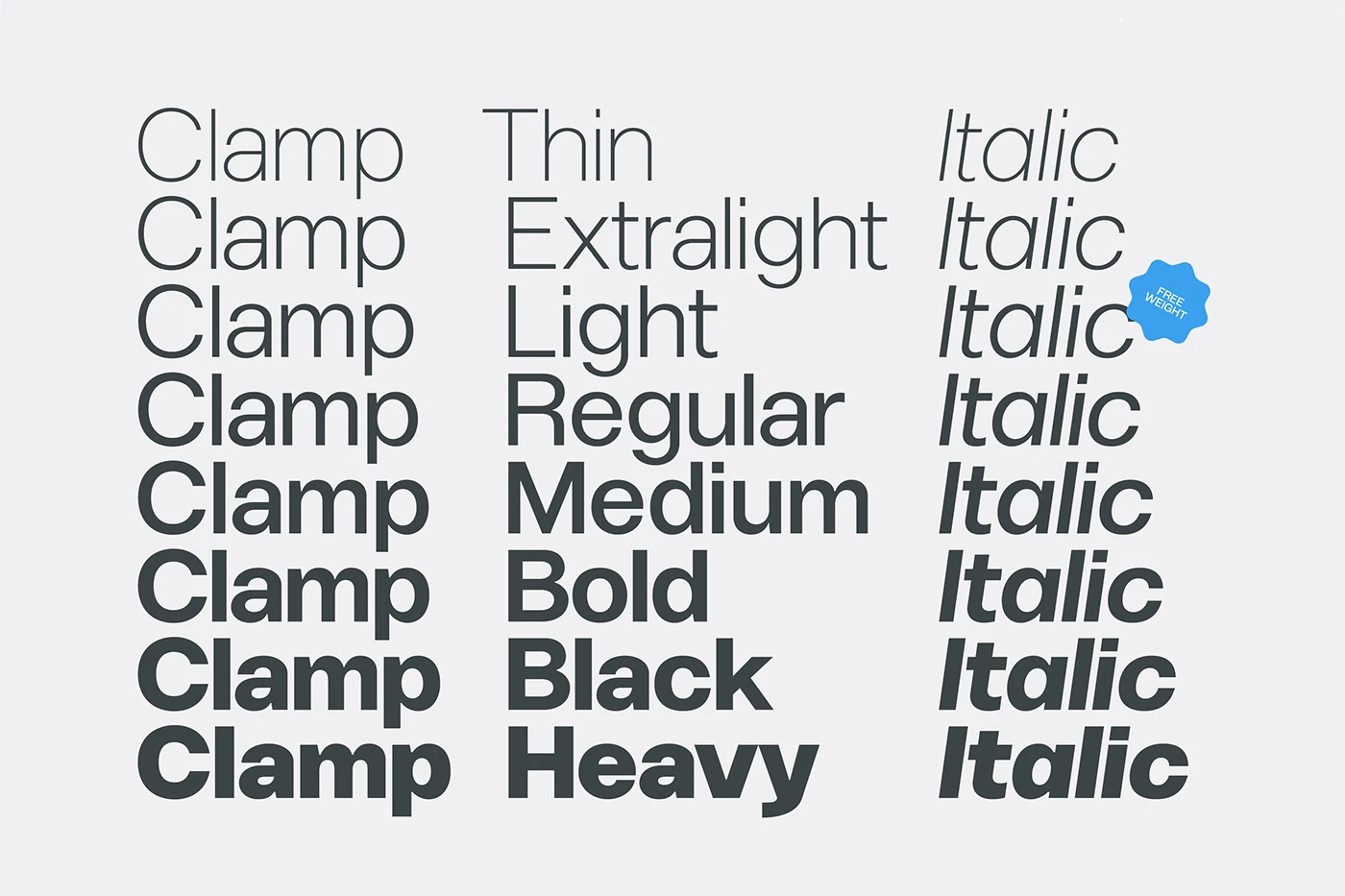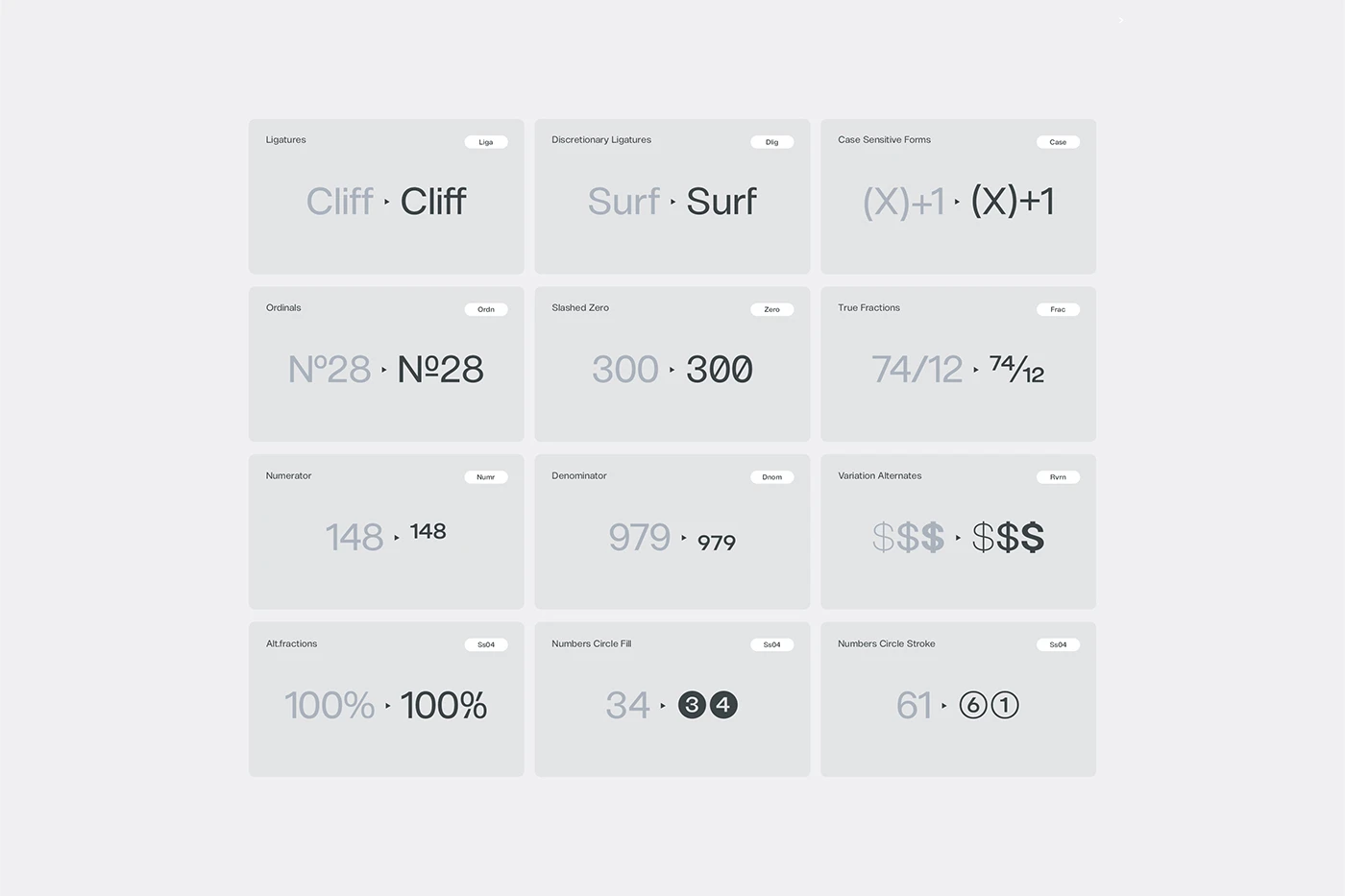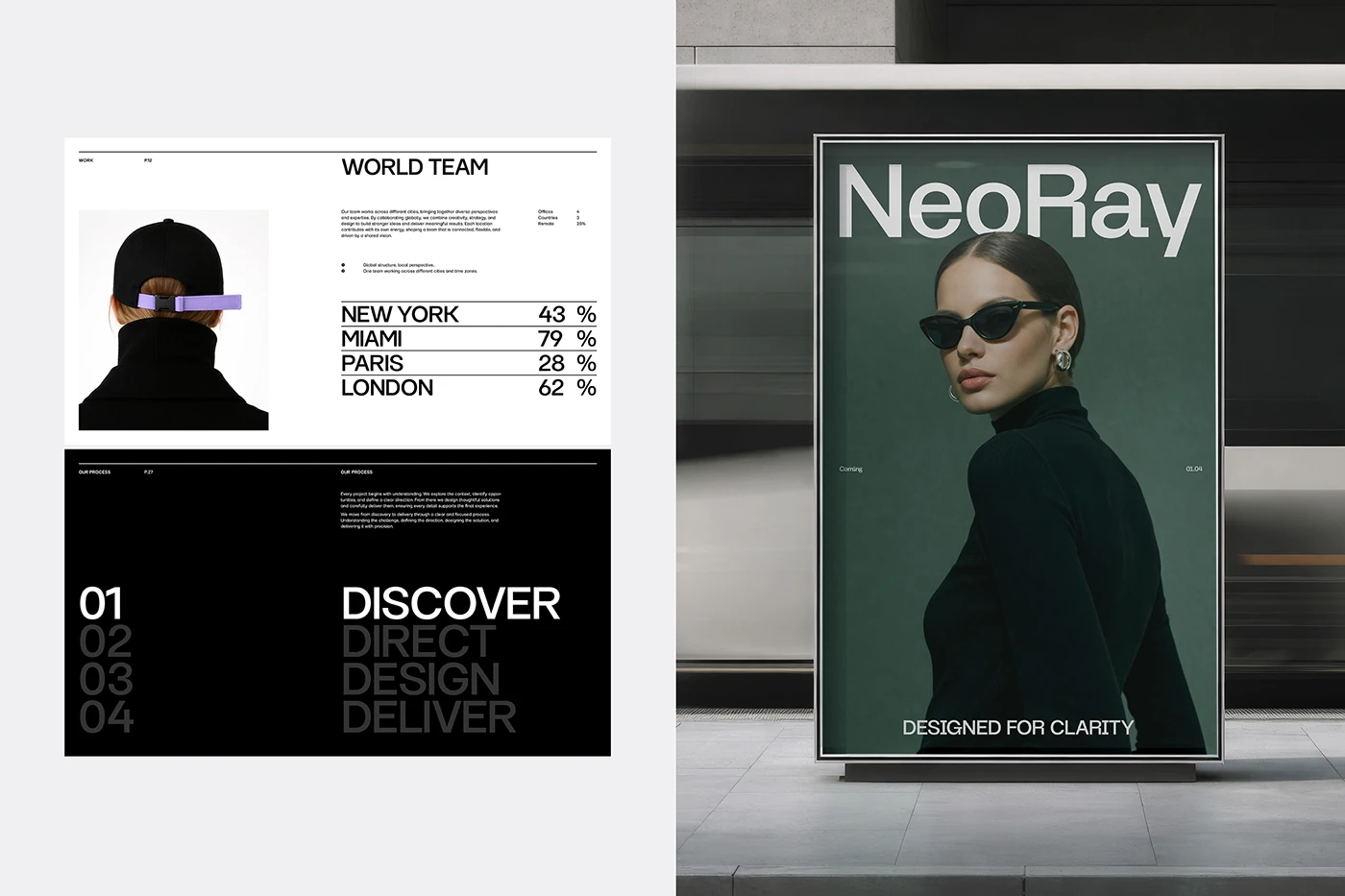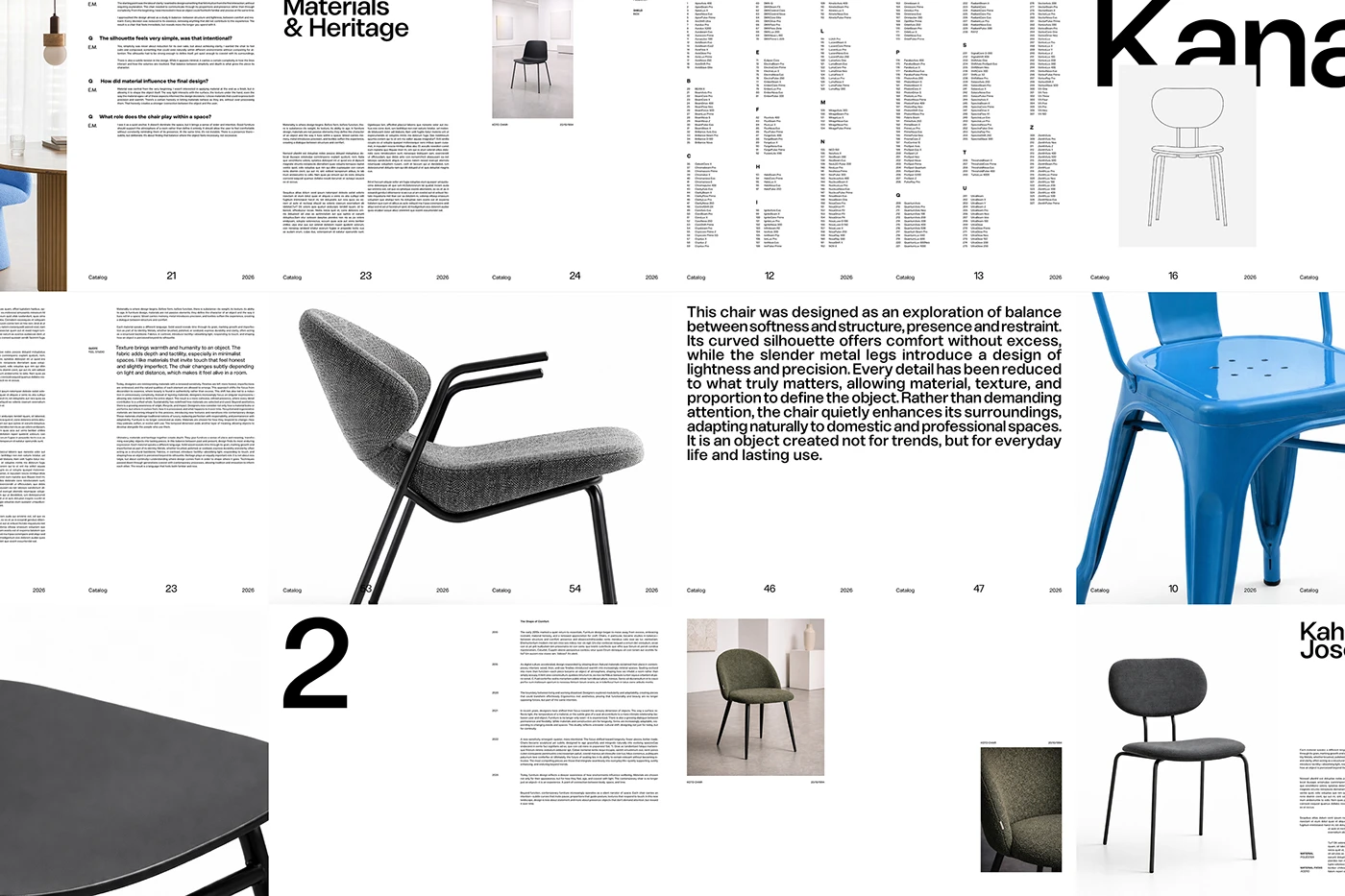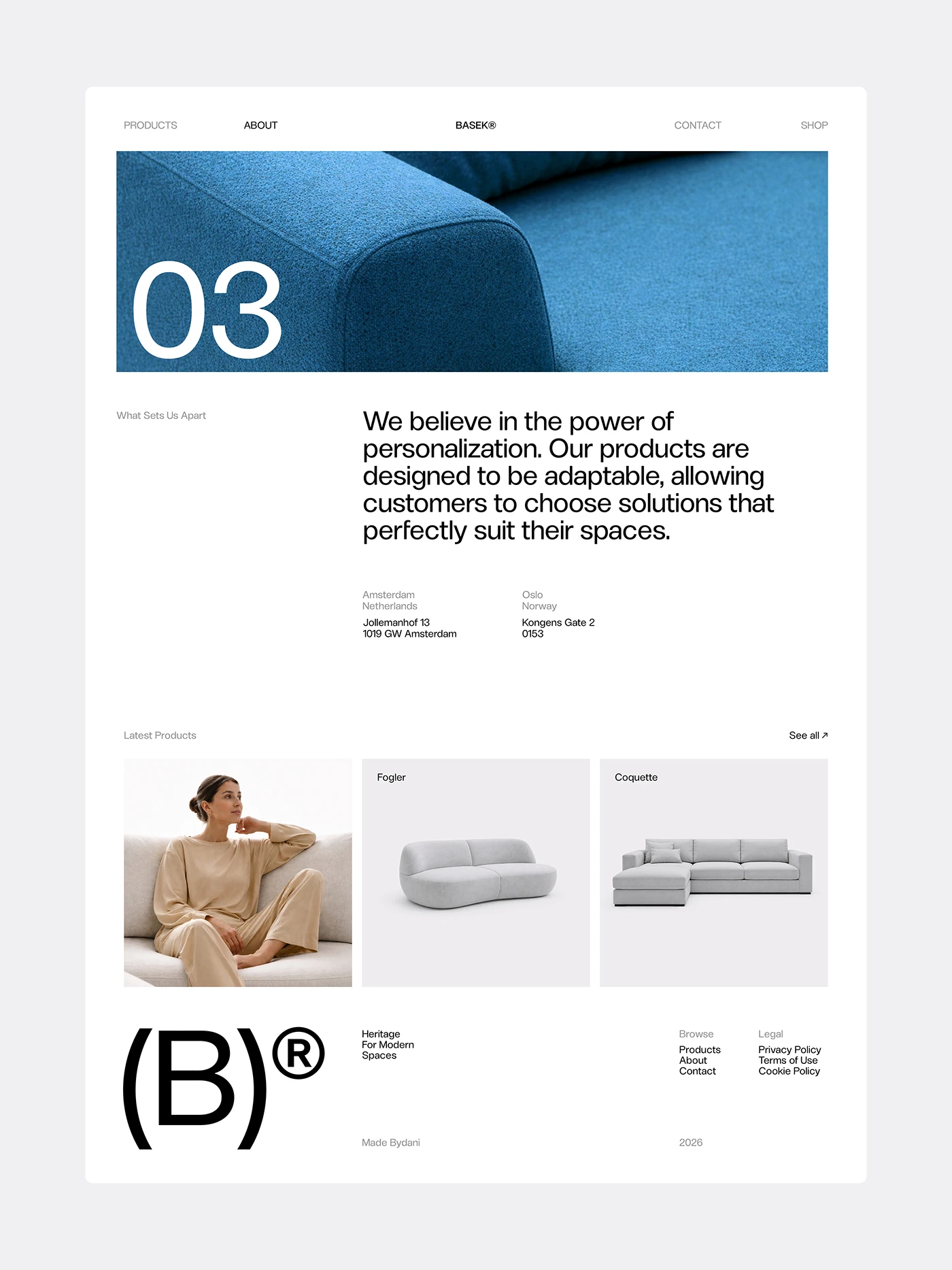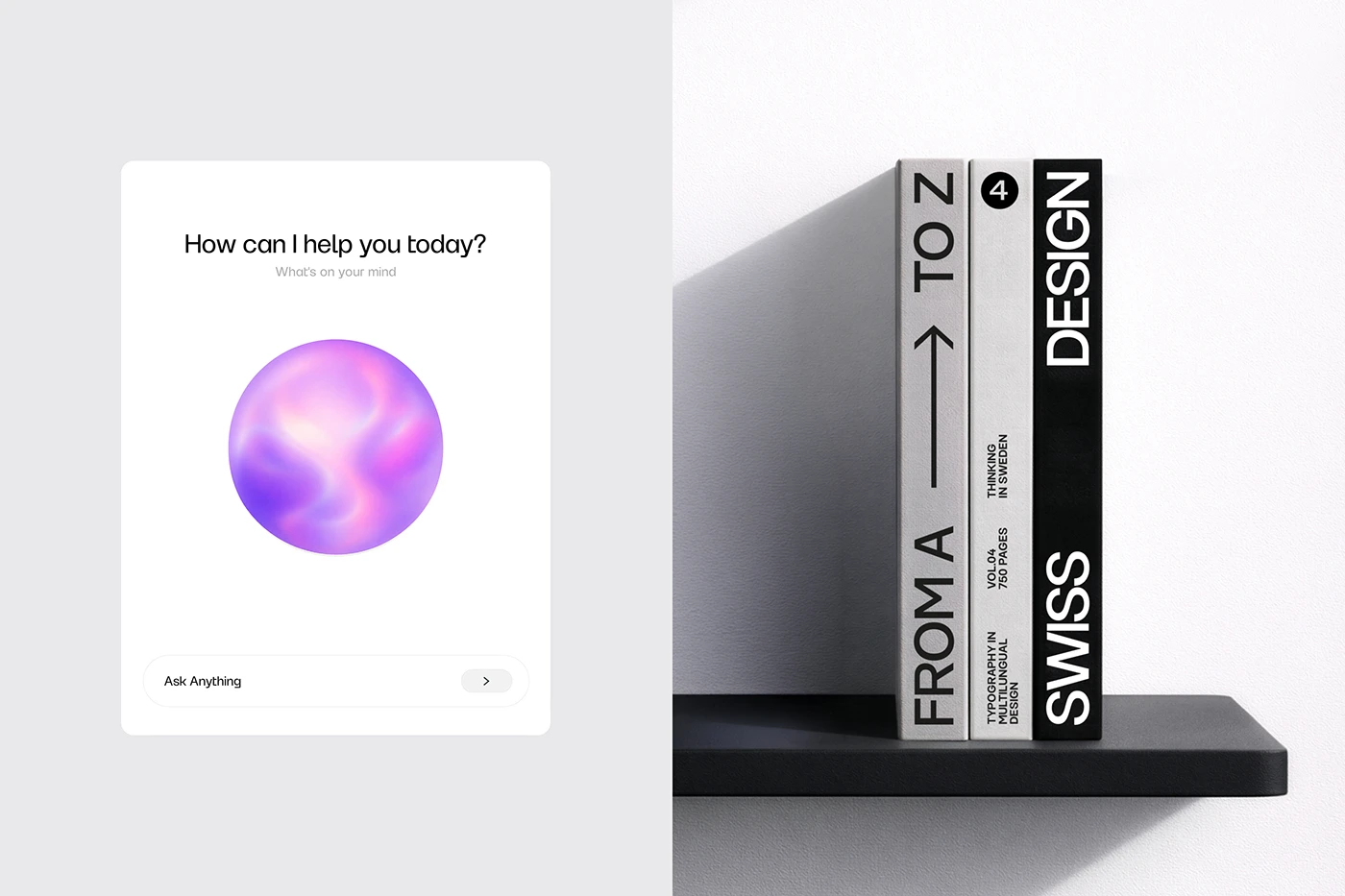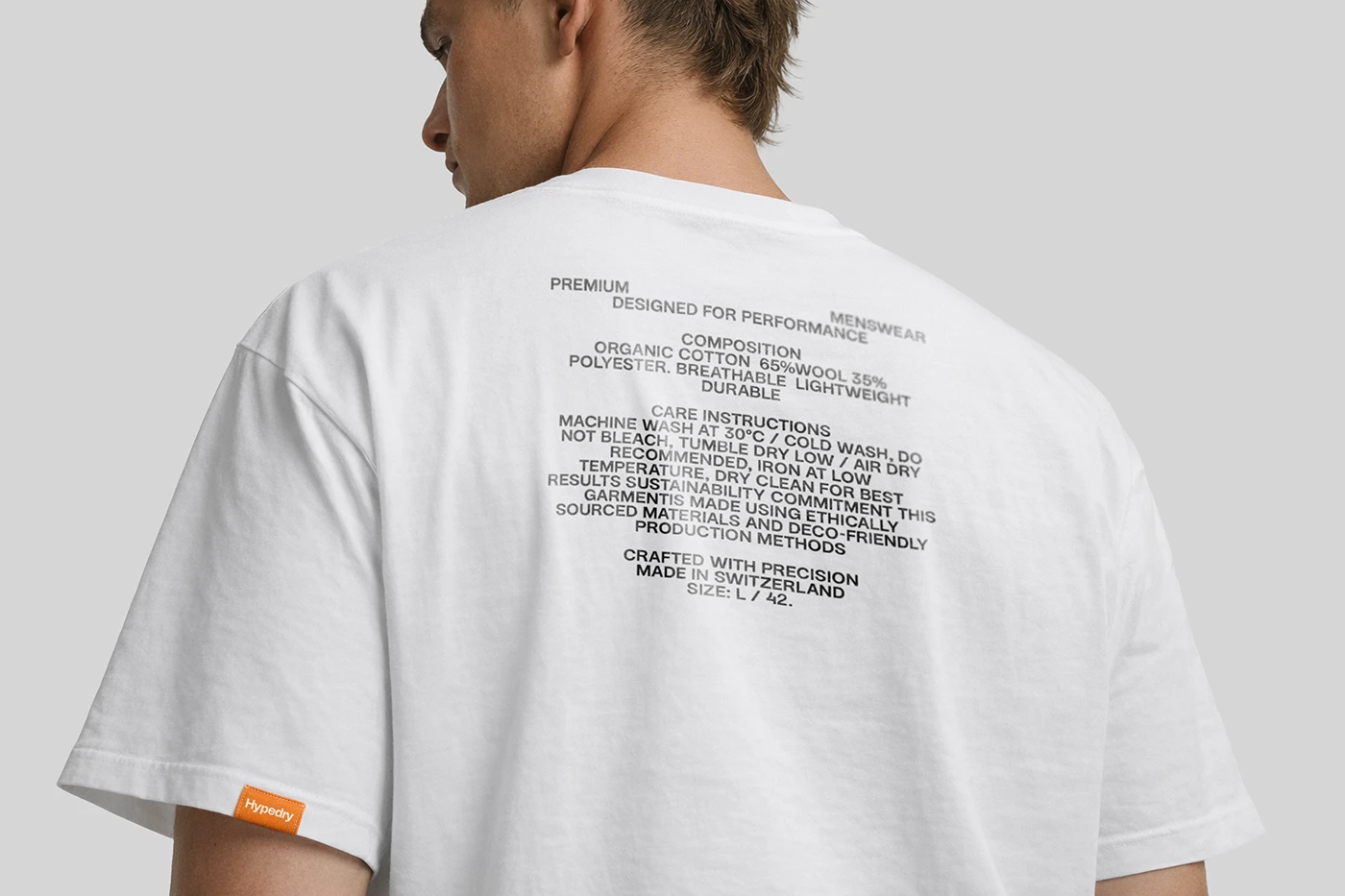
Clamp Font Family là bộ font chữ display có độ tương phản cực kỳ cao với những đường nét hình khối góc cạnh mang đậm tính công nghiệp, được tạo nên từ bàn tay thiết kế của TypeFoundry Studio.
Đội ngũ thiết kế đã xây dựng một hệ thống font chữ modular vô cùng vững chắc để định hình toàn bộ phong cách trực quan cho dự án này. Sự kết hợp giữa sắc đen sâu của các trang giới thiệu (specimen sheets) và màu trắng stark tương phản của các chữ cái tạo nên một bố cục typography vô cùng ấn tượng trên các trang poster và tạp chí. Bộ font này dựa trên một kiểu chữ sans-serif cấu trúc nặng (heavy), cân bằng hoàn hảo giữa độ chính xác cơ khí và các lưới layout hiện đại. Khi kết hợp những chữ cái kỹ thuật số chuẩn chỉnh này với khoảng cách kerning cực kỳ chặt chẽ, tổng thể thiết kế mang lại một cảm giác căng tràn năng lượng. Từng asset trong layout đều được căn gióng nghiêm ngặt theo hệ thống lưới dọc (vertical grid), giúp tạo nên trật tự cấu trúc và phân cấp thị giác rõ ràng, giữ cho bố cục không bị rối mắt.
Nét tiết chế công nghiệp trong thiết kế Typography Display
Hệ thống thiết kế của bộ font này đã khéo léo chuyển hóa cơ chế kẹp cơ khí thành các điểm chạm kỹ thuật số thông qua những quyết định tạo hình chữ cái tinh tế. Các trang giới thiệu font sở hữu độ phủ mực dày và các góc bo tròn sắc nét, mang lại cảm giác chạm (tactile) rất thật cho các ma trận ký tự đơn giản. Sự đối lập giữa bề mặt giấy tối màu và đường viền chữ trắng sắc sảo mang lại nhiều cảm hứng, cho thấy đồ họa thương mại vẫn có thể tạo được độ chất riêng mà không cần phụ thuộc vào các hoa văn trang trí cầu kỳ. Các bảng tra cứu glyph và poster giới thiệu đều ưu tiên khoảng trắng rộng rãi cùng cấu trúc lưới sạch sẽ, giúp cho toàn bộ tài nguyên thị giác trở nên vô cùng đồng bộ.
Tóm lại, bộ font family này giúp các nhà thiết kế editorial đơn giản hóa việc tạo ra các tiêu đề lớn có sức nặng và phân cấp rõ ràng. Đội ngũ thiết kế đã thành công trong việc tạo ra một layout typography vừa chuyên nghiệp vừa hiện đại. Hệ thống lưới sạch sẽ đảm bảo rằng các nét chữ dù có dày và sát nhau đến mấy thì vẫn cực kỳ dễ đọc khi nhìn lướt qua. Lựa chọn layout này biến các ấn phẩm editorial thành một công cụ thị giác đáng tin cậy. Dự án cũng cho thấy phong cách tối giản có chiến lược hoàn toàn có thể hiện đại hóa các nhãn tiện ích của doanh nghiệp. Để xem thêm chi tiết về bộ nhận diện trực quan này, mọi người có thể ghé qua www.behance.net/gallery/251224331/Clamp-Font-Family.
The Clamp Font Family is an ultra-high contrast display typeface packed with edgy, blocky shapes and a heavy industrial vibe, beautifully crafted by TypeFoundry Studio.
The design team built a rock-solid modular type system to shape the entire visual direction of this project. The mix of deep, rich blacks in the specimen sheets against the stark white contrast of the letterforms creates an absolutely striking typographic layout across posters and magazine pages. Based on a heavy sans-serif structure, this font perfectly balances mechanical precision with modern layouts. When these ultra-clean digital glyphs pair up with super tight kerning, the overall design just bursts with energy. Plus, every layout asset is strictly aligned to a vertical grid, creating clear structural order and visual hierarchy that keeps everything looking sharp and clutter-free.
Industrial Restraint in Display Typography Design The design system cleverly translates mechanical clamping mechanisms into digital touchpoints through subtle letterform choices. The specimen pages feature heavy ink coverage and sharp yet rounded corners, giving a wonderfully tactile feel to the clean character matrices. The contrast between dark paper surfaces and crisp white outlines is incredibly inspiring, proving that commercial graphics can have tons of character without relying on fussy ornamentation. Both the glyph maps and promotional posters prioritize generous white space and clean grid structures, ensuring all visual assets look beautifully cohesive.
In short, this font family makes it a breeze for editorial designers to create massive, impactful headlines with a crystal-clear hierarchy. The design team nailed a typographic layout that feels both professional and fresh. The clean grid system ensures that even with thick strokes and tight spacing, everything stays super readable at a glance. This layout choice transforms editorial print pieces into reliable visual tools. The project also proves that strategic minimalism can completely modernize corporate utility labels. To check out more details on this visual identity, head over to the www.behance.net/gallery/251224331/Clamp-Font-Family.